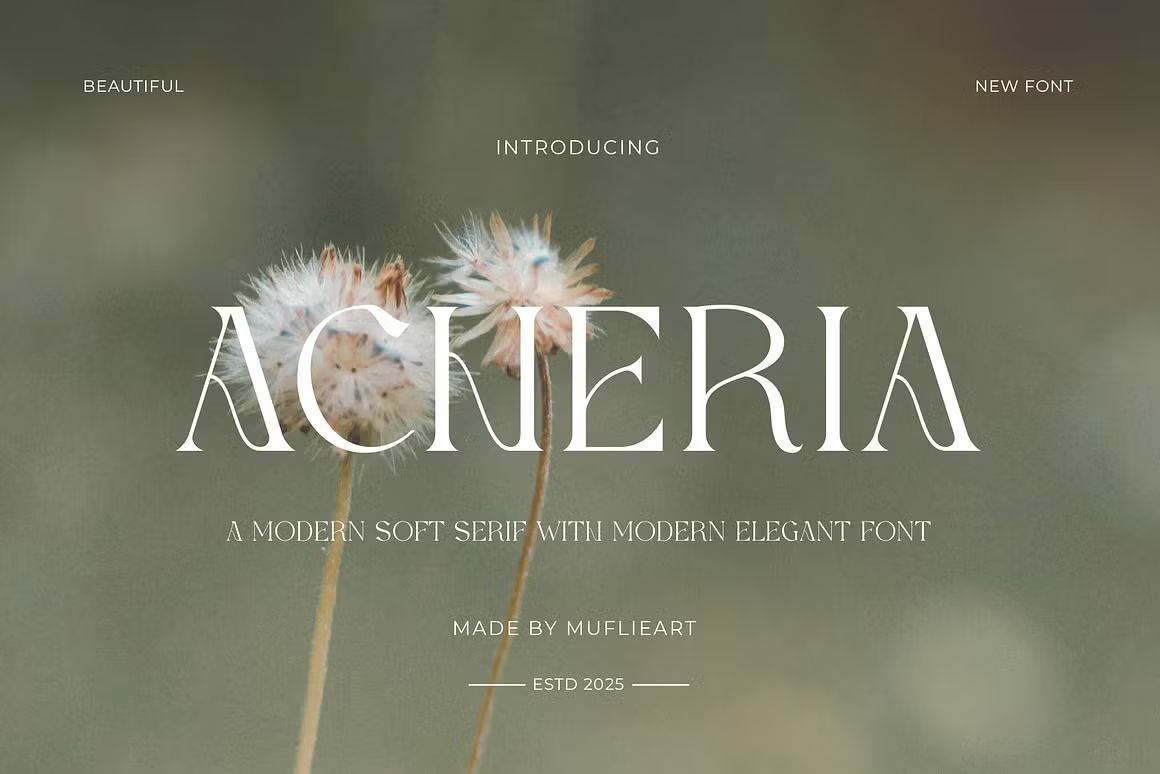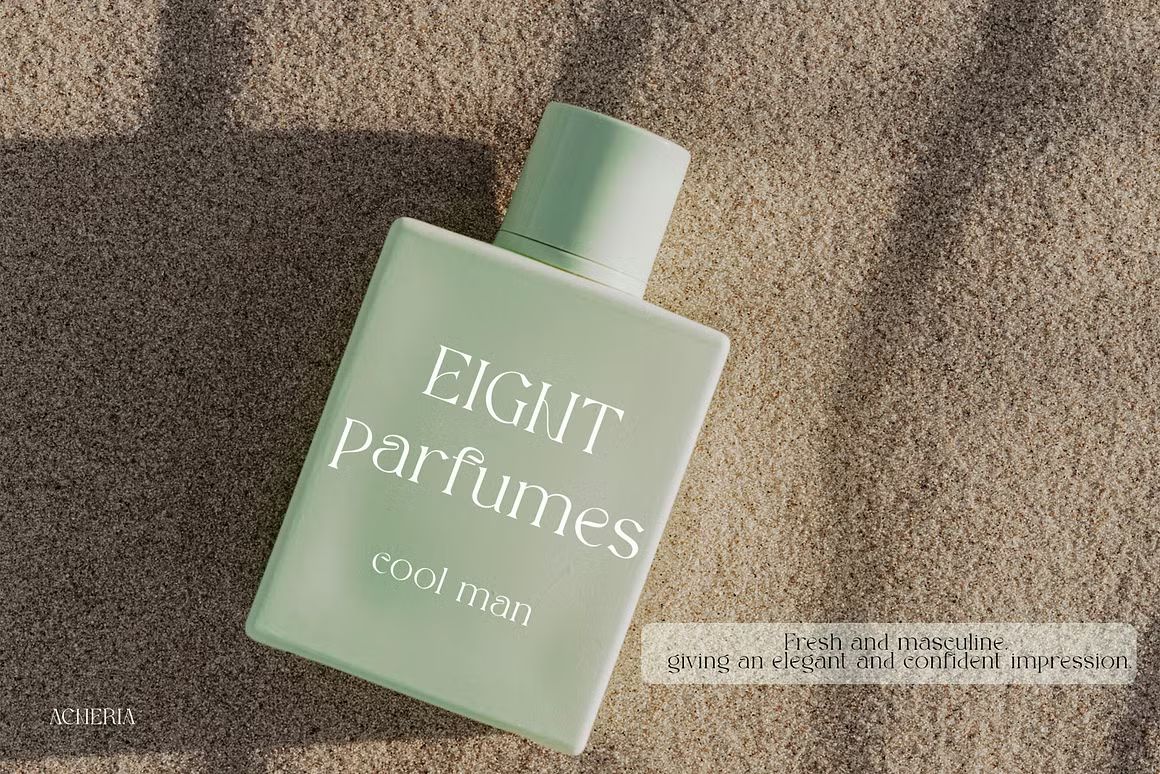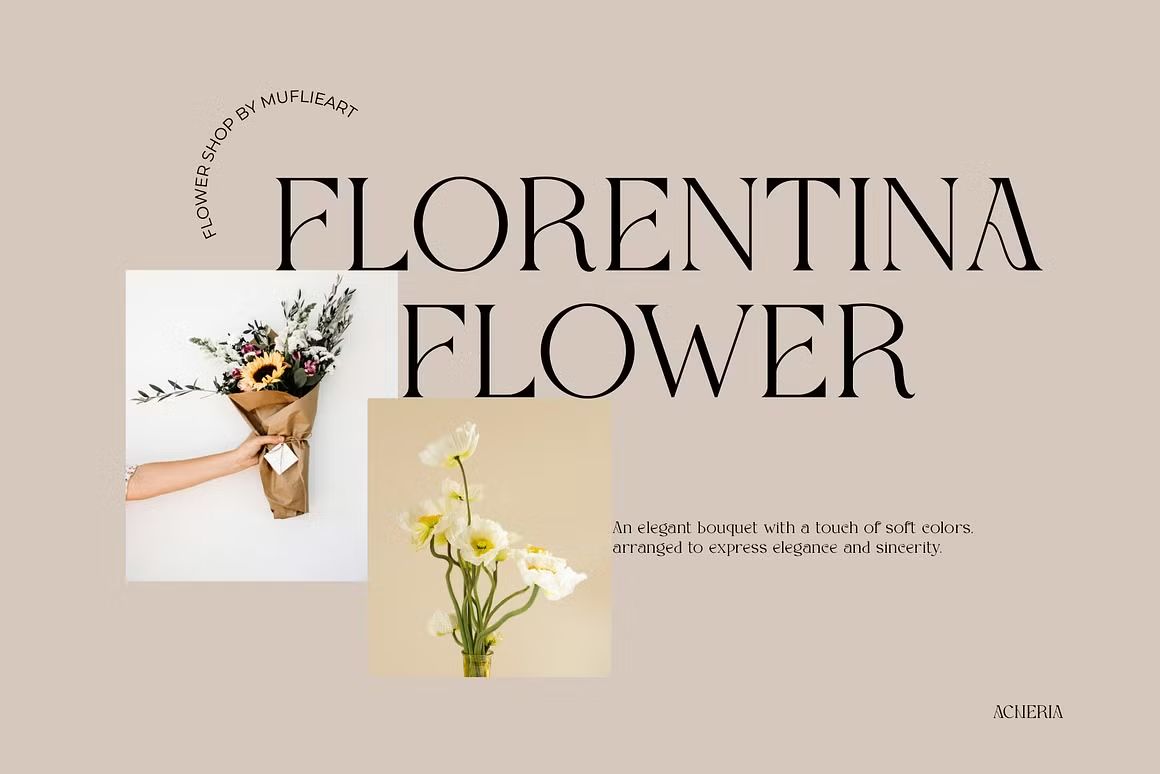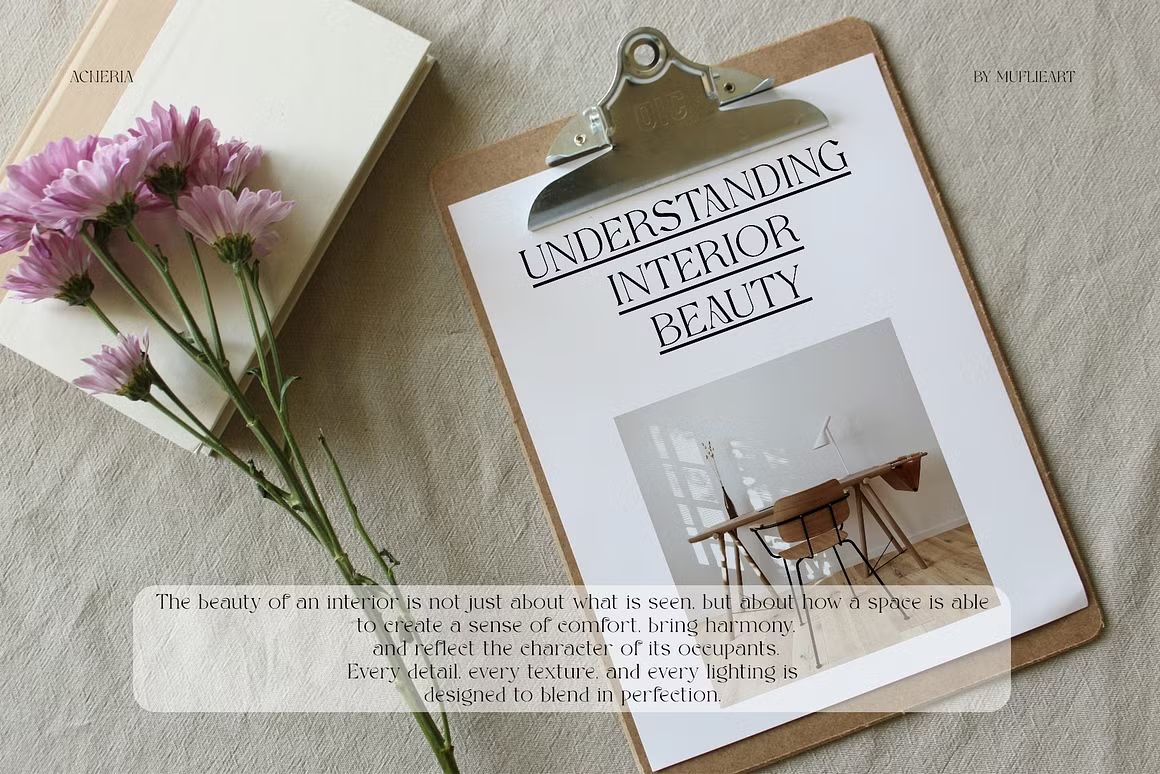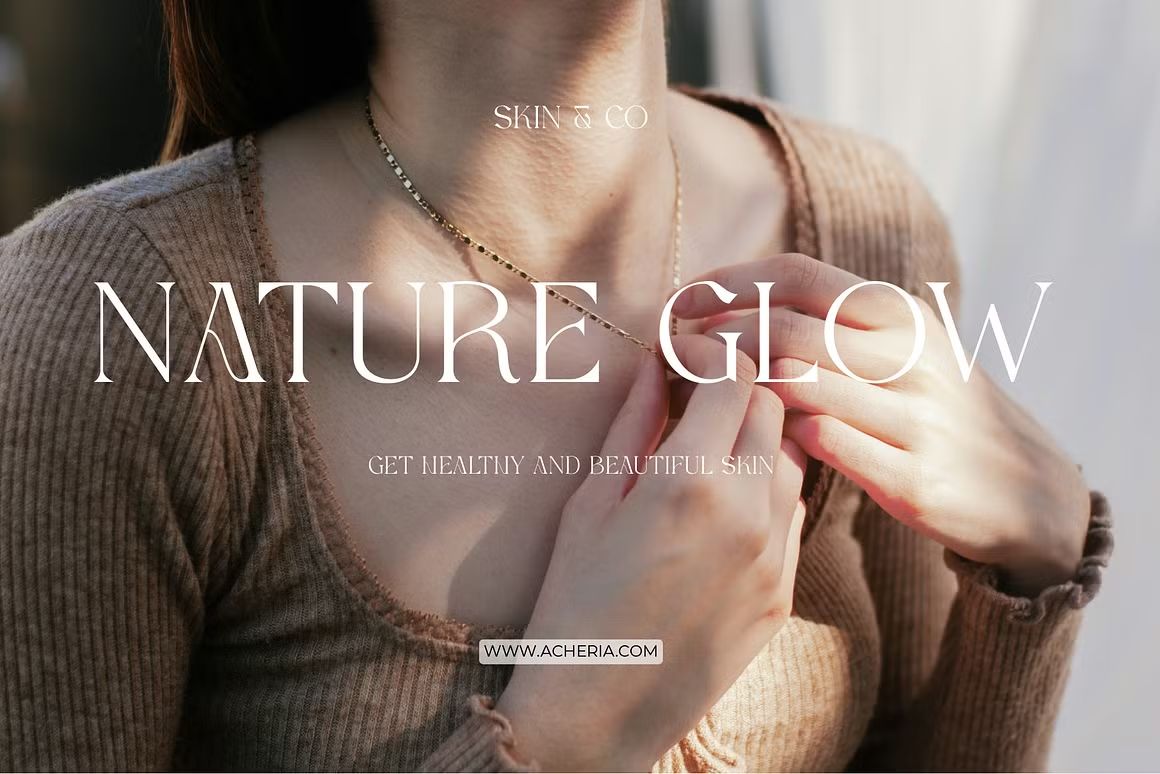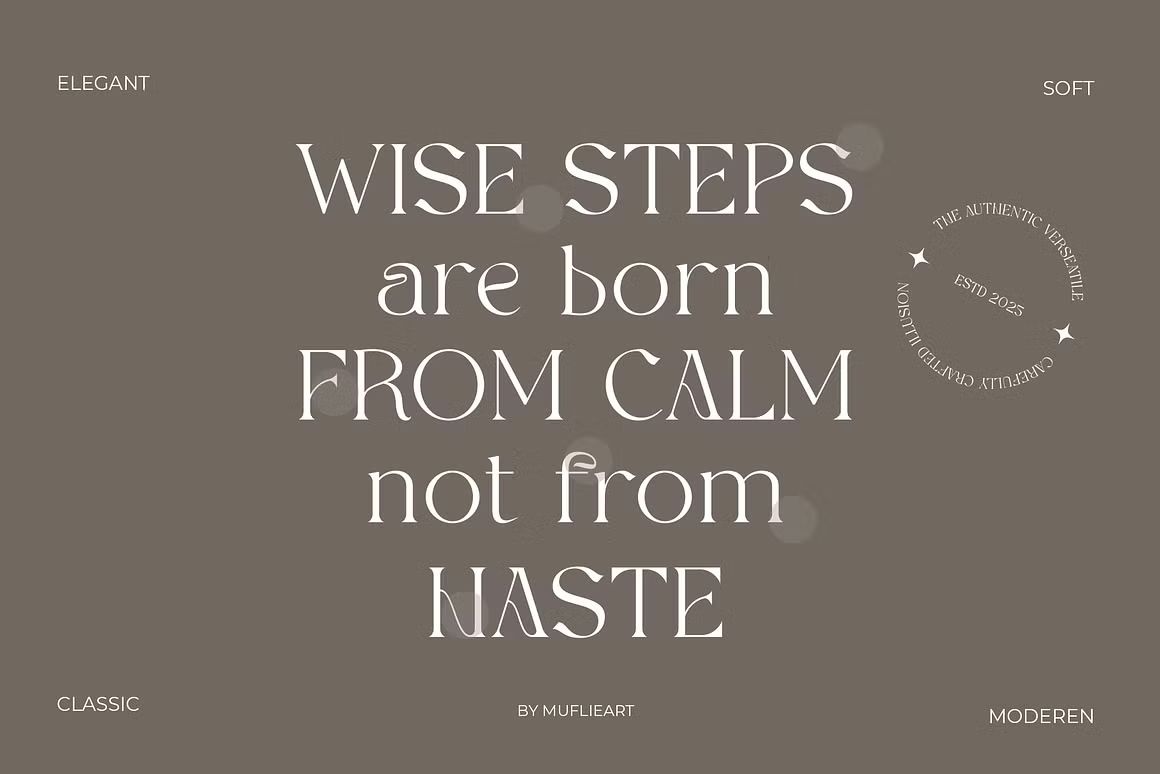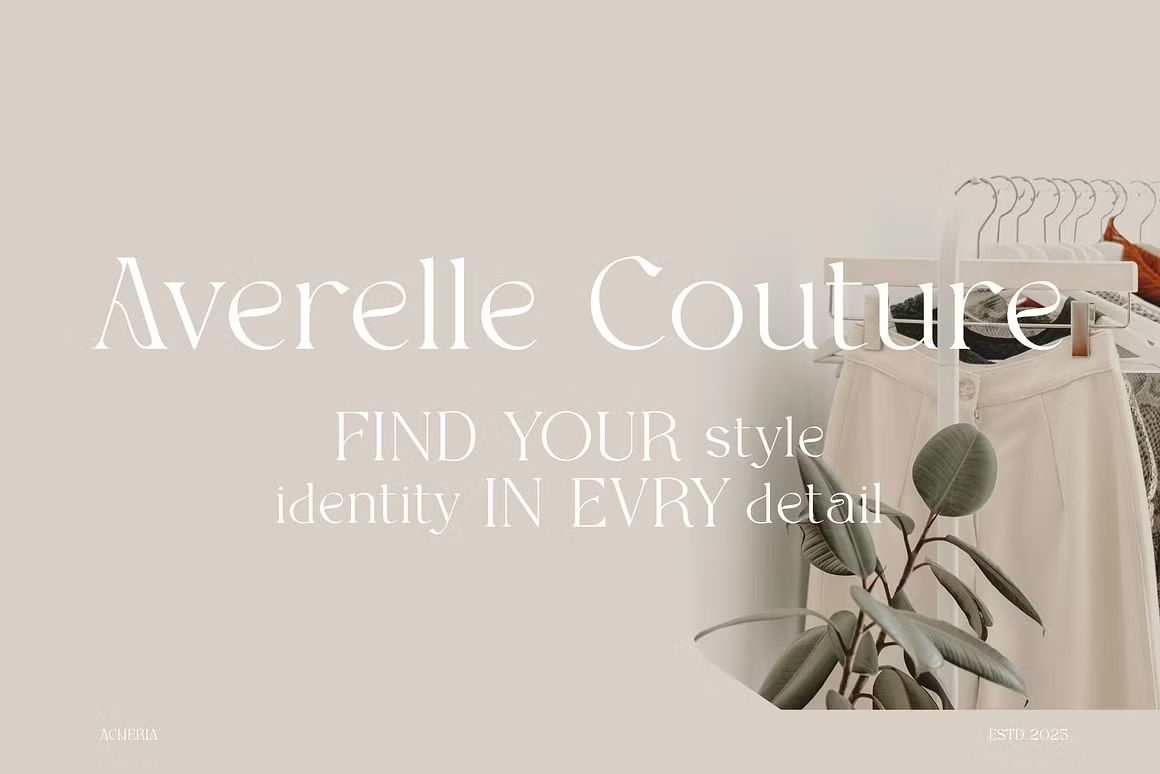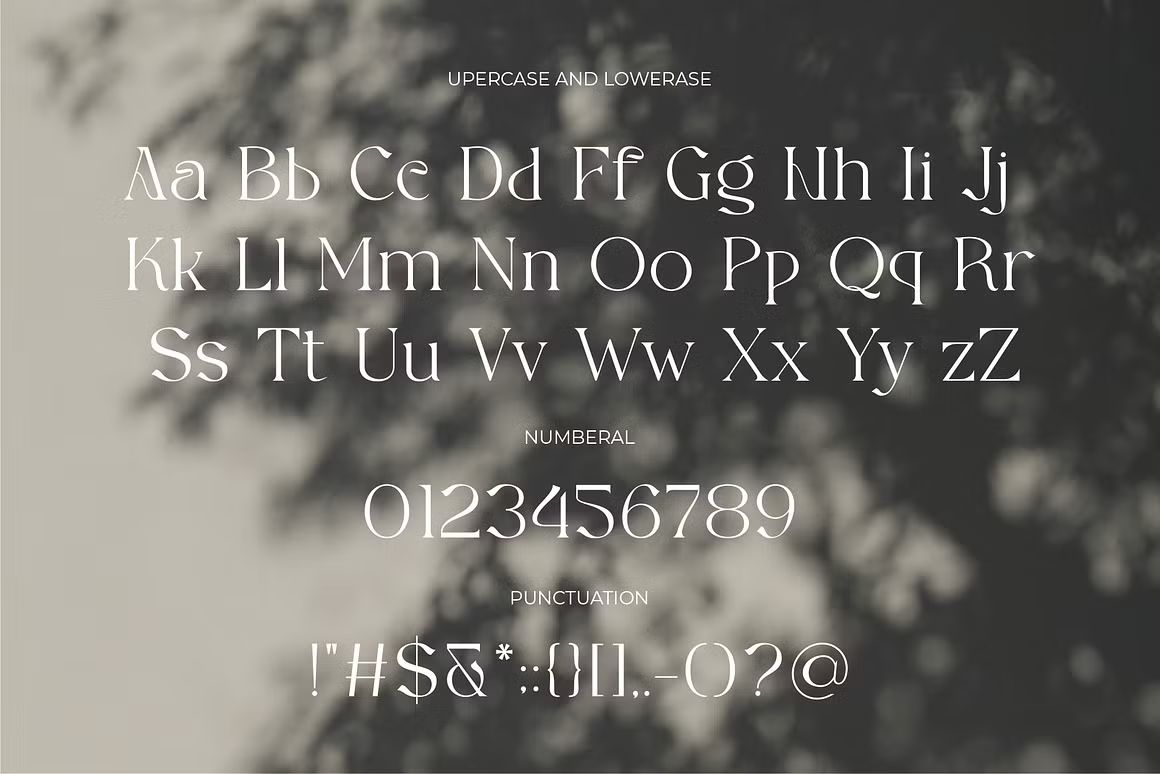
Acheria – Sans Serif Font
Acheria adalah font sans serif modern dengan garis bersih, proporsi seimbang, dan tampilan elegan. Desainnya yang minimalis namun kuat menjadikannya cocok untuk berbagai kebutuhan desain seperti branding, editorial, kemasan produk, desain digital, dan presentasi profesional. Acheria menawarkan fleksibilitas tinggi dengan nuansa kontemporer yang stylish dan profesional.
• Sans serif modern dan serbaguna
• Ideal untuk branding, editorial, dan desain digital
• Termasuk huruf kapital, kecil, angka, dan simbol